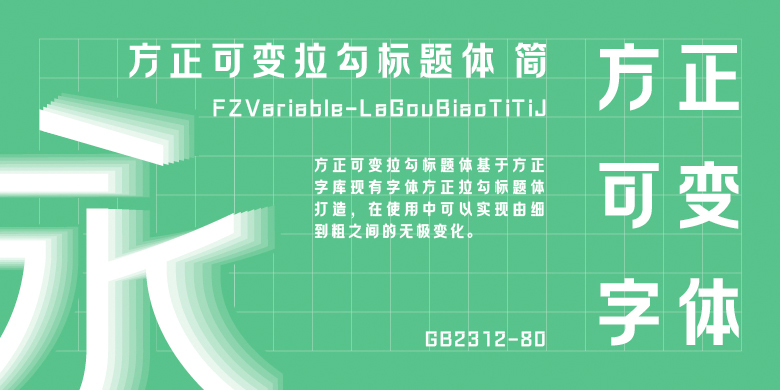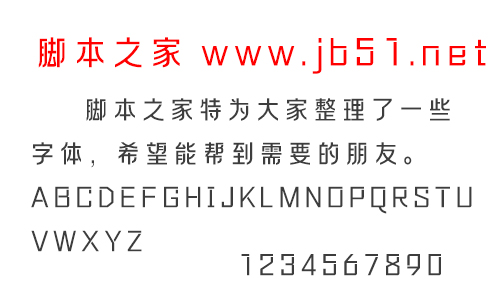
方正可變拉勾標題體是針對互聯(lián)網(wǎng)活動、廣告、報刊等媒介而設計的一款標題字庫;高重心,筆劃拐角處進行圓滑處理,使其更具美感和豐富性。方正可變拉勾標題體支持文字粗細無級調(diào)節(jié),設計師通過調(diào)整字重軸(Weight)的變化,可以實現(xiàn)字形的平滑連續(xù)的細微調(diào)整,滿足不同版式的設計需求。整體字型吸收民國老字體特點,工整、多彩,保留其韻味注入新時代活力,煥然一新,適用于現(xiàn)代及復古等應用。歡迎喜歡方正可變拉勾標題體的朋友前來下載使用。